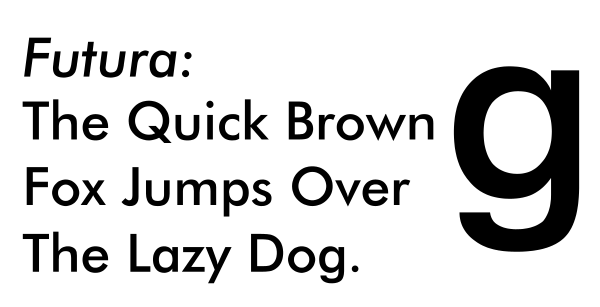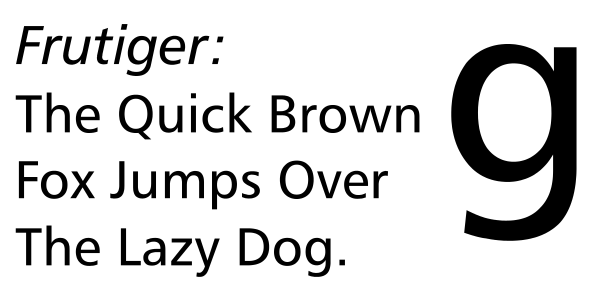
Гротеск (шрифт)
Гроте́ск, ру́бленый шрифт (брит. англ. sans serif, от фр. sans — «без» и англ. serif — «засечка») — шрифт без засечек[1]. В более точной и развёрнутой формулировке: «Гарнитура шрифта, подобного египетскому, с равной толщиной всех штрихов, но, в отличие от египетского шрифта, без засечек и с максимальной насыщенностью строки, создающей напряжённое впечатление… Отсюда название»[2].
История и общая характеристика
Первый наборный шрифт этого класса был создан в 1816 году. Он применялся для привлечения внимания в рекламе и типографских заголовках. Основоположником современных типографских универсальных гротесков считается шрифт «акциденц-гротеск», разработанный в 1896 году неизвестным художником фирмы «Berthold». В XX веке гротески применялись как для акциденций (так называются дополнительные элементы типографского набора), так и для сплошного текста. Среди так называемых «рубленых шрифтов» в XX веке наибольшее распространение получили шрифты — «франклин готик» (1905), «гельветика» (1957), «универс» (1957). Гротески считаются основной шрифтовой гарнитурой Швейцарского стиля.
Старые гротески
Геометрические гротески
Гуманистические, динамические гротески
Гуманистические гротески возникли как ответ геометризму ранних гротесков. При разработке таких шрифтов использовались наработки из антикв старого стиля. Такие шрифты обычно имеют небольшой контраст и открытый рисунок.